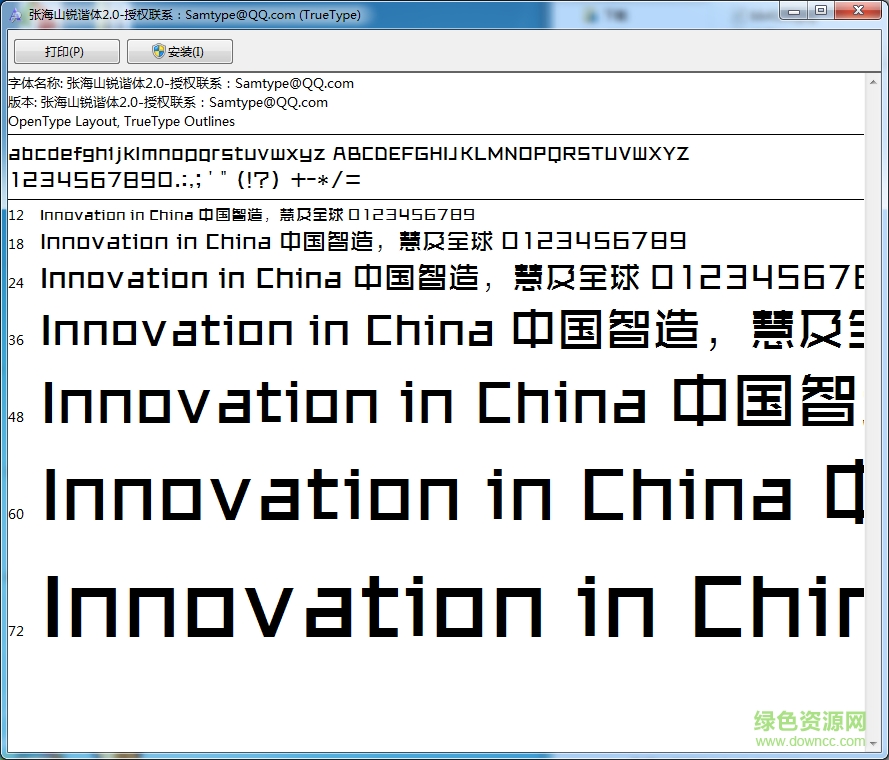
張海山銳諧體2.0是一款免費(fèi)好用的電腦字體,字體典雅高端大氣,粗細(xì)均勻整體效果極具美感,使用領(lǐng)域廣泛深受廣大用戶喜愛(ài)??靵?lái)綠色資源網(wǎng)下載體驗(yàn)吧!
張海山銳諧體2.0風(fēng)格非常獨(dú)特,筆畫輕盈,點(diǎn)畫精致,轉(zhuǎn)折十分舒展嗎,常常用于各類海報(bào)、雜志、書刊或廣告中!